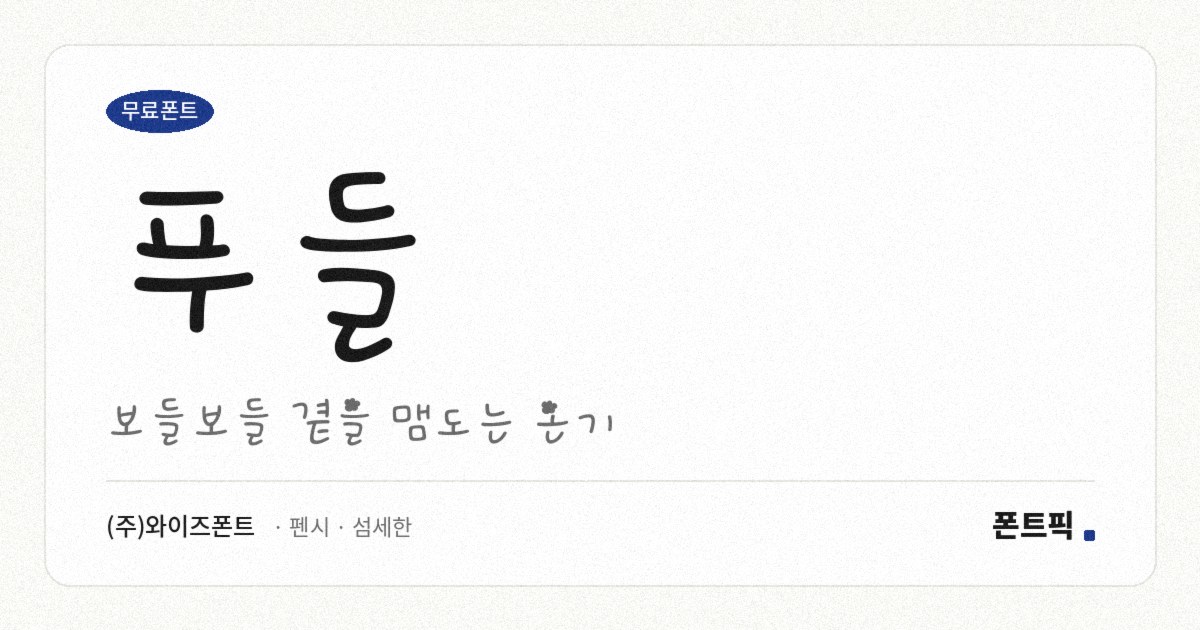
푸들
TDTDPoodle
푸들 소개
군데군데 발바닥 자국이 찍혀 있는 손글씨 서체입니다. 랑처럼 획이 비는 자리에 발자국이 들어가 있어, 반려동물 계정 이름이나 산책·분양 안내처럼 소재가 맞는 자리에서 힘을 냅니다.
같은 회사의 손글씨 서체 가운데 가장 가볍습니다. 자면을 채우는 비율이 0.096으로 폰트픽에 올라온 같은 굵기의 한글 서체 138종 중 아래에서 열한 번째이고, 가로획이 세로획보다 1.5배 가까이 굵어 획이 옆으로 눌려 있습니다. 받침이 붙을 때 글자가 0.36em이나 아래로 내려가는 탈네모틀이라 글줄의 높낮이 차도 큰 편입니다.
획이 얇은 만큼 배경이 복잡하면 묻히니 여백을 넉넉히 두고 쓰세요. 작게 쓰면 발자국 장식도 뭉개져 알아보기 어려워지니 크게 쓰는 편이 좋습니다. 현대 한글 11,172자를 모두 담았고 굵기는 하나입니다.